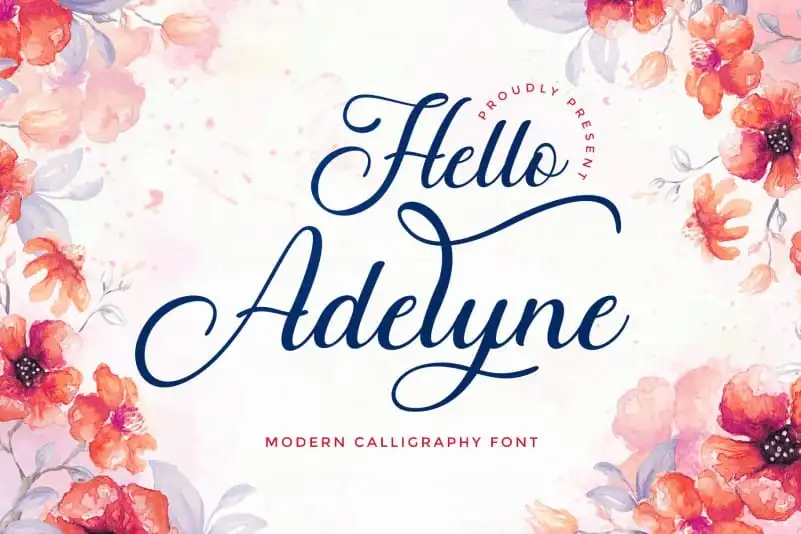
Hello Adelyne Calligraphy Font – Download Grátis
Introduzimos a fonte “Hello Adelyne Calligraphy Font”, uma elegante tipografia de casamento moderna e feminina. Desenvolvida por Rantautype, esta fonte incorpora um toque artesanal e misturado com o contemporâneo. Ideal tanto para trabalhos profissionais quanto para trabalhos pessoais, ela é perfeita para criar designs agradáveis como água-marinha em organizadores de casamentos, assinaturas ou identidade visual, citações, capas de álbum ou cartões de convite. A adébil natureza e mistura moderna deste tipo de letra complementam um design com estilo. É perfeita para qualquer projeto gráfico.